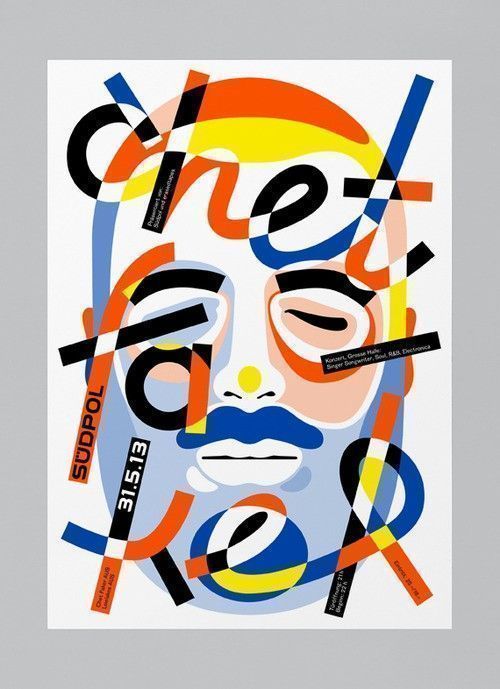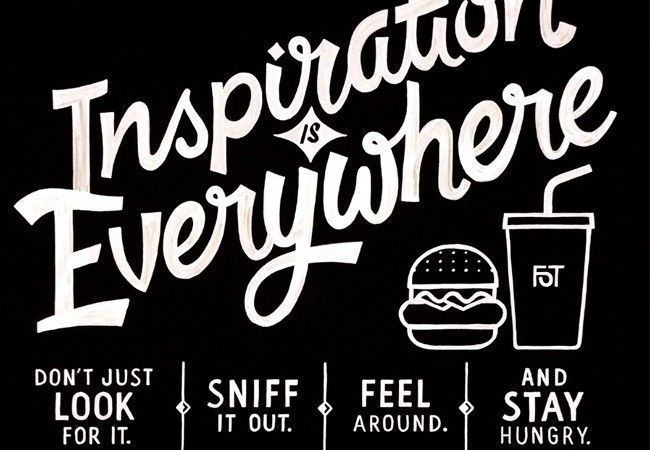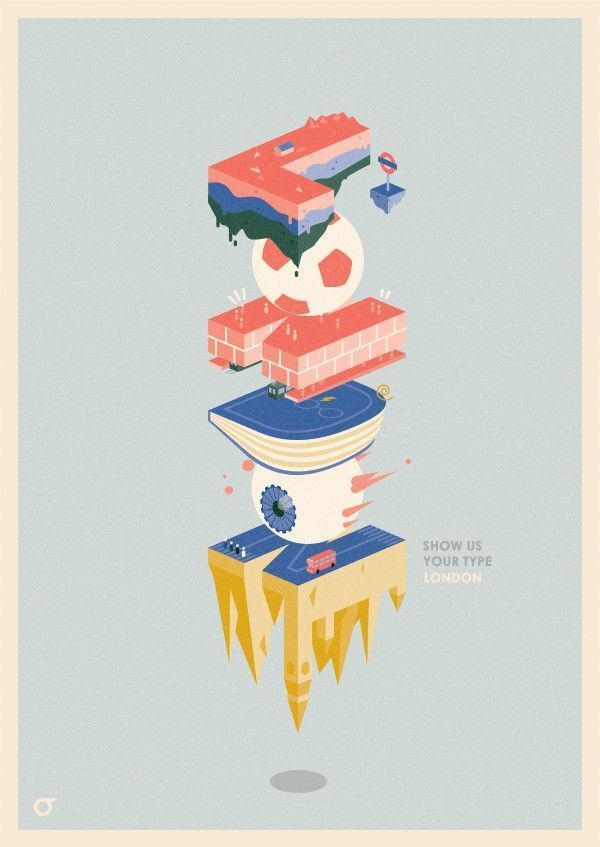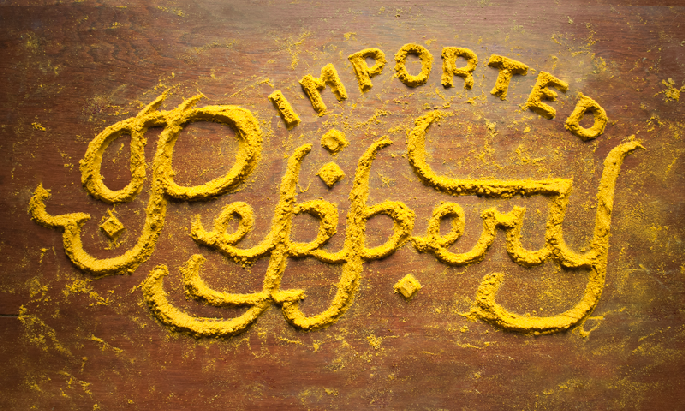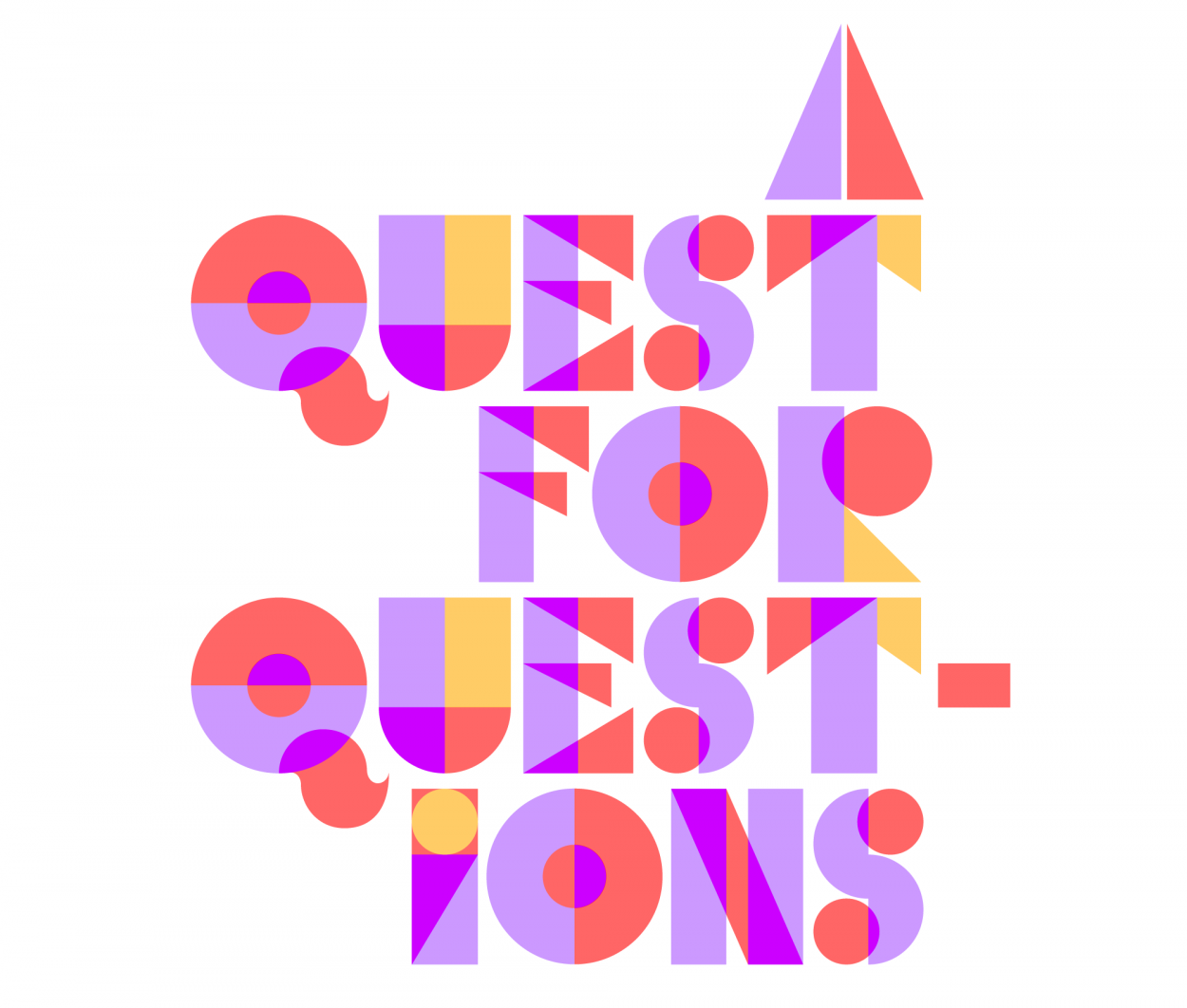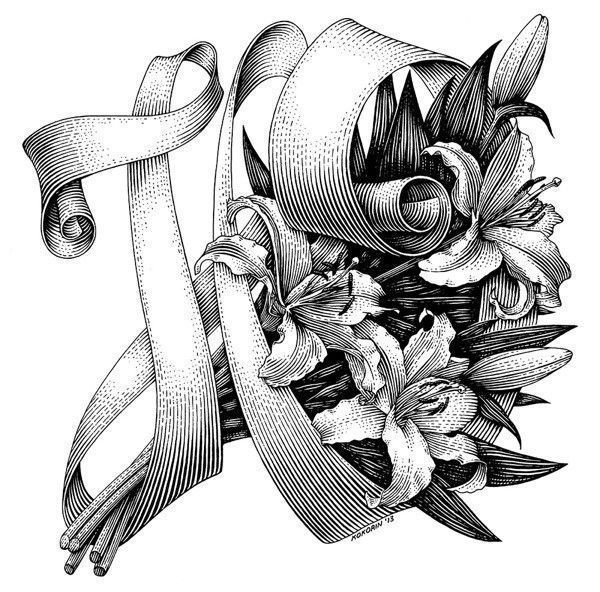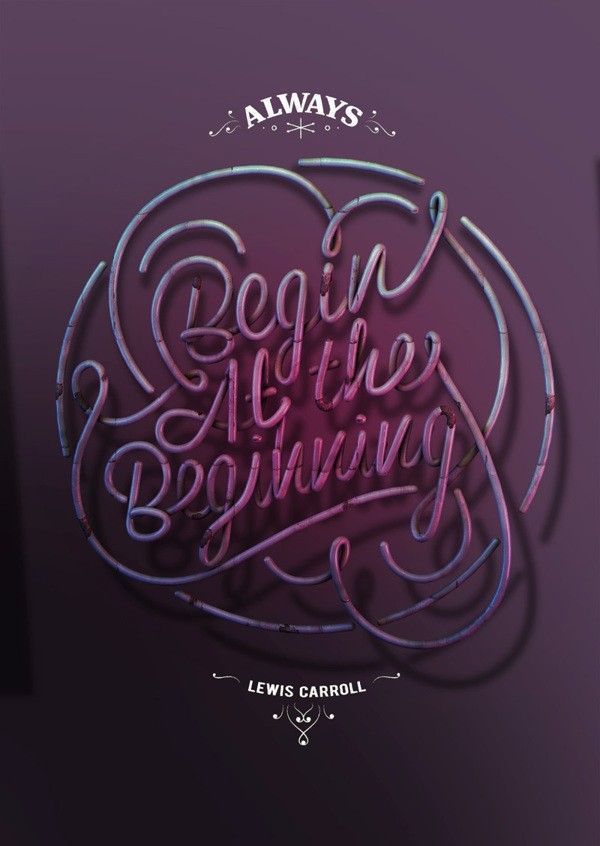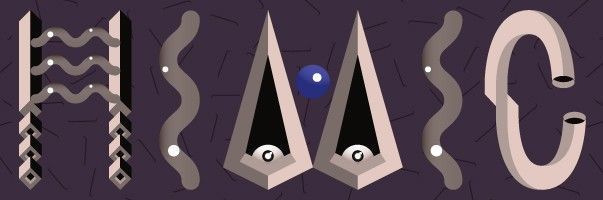
Passe l’inspirateur ! Vol.2 : Typographie
« Passe l’inspirateur ! » c’est un rendez-vous quasi-quotidien puisqu’on se retrouvera 5 jours par semaine pour découvrir ensemble les créations graphiques à ne pas rater. Le jeudi, c’est la typographie qui est à l’honneur.
► « The Letters IO », un travail de type gravure réalisé par le russe Andrey Kokorin pour le shop en ligne ici et son site par là
► La ville de Londres vue par le graphiste coréen, Onasup. Un poster très cool pour dé-Corée (ndlr : hihi). Le site par là
► « Mimic » est une typo créée par Beta pour le site YouWorkForThem. Parfaite pour mettre de la drogue hallucinogène dans nos artworks. Le site ici
► Le petit Suisse, Feixen, est en charge de la communication visuelle pour les événements du centre culturel Südpol et nous pond des affiches toujours plus originales. Son site par là
► Danielle Evans, aussi connue connue sous le nom de Marmalade Bleue, est une typographe et designer américaine qui a lancé un projet consistant à produire de la typographie à partir de nourriture. Le site ici
► C’est l’histoire d’un père qui demande à son ami, David Gonzalez, de créer un petit artwork pour fêter la réussite de son fils à son examen de fin d’année. Le site ici
► Quand l’agence anglaise Shotopop décide de mettre en image une citation d‘Alice au pays des merveilles ça donne ça. Le site par là
► Les « amis de la typo » ont encore frappé. Comme d’habitude un travail de qualité dont on a l’habitude de voir de la part de cette équipe de génies. Leur site ici
► Le très talentueux Nairone nous propose cette petite vidéo où il nous montre le déroulement de la création de l’identité visuelle du bar parisien : Workshop. Son site juste là